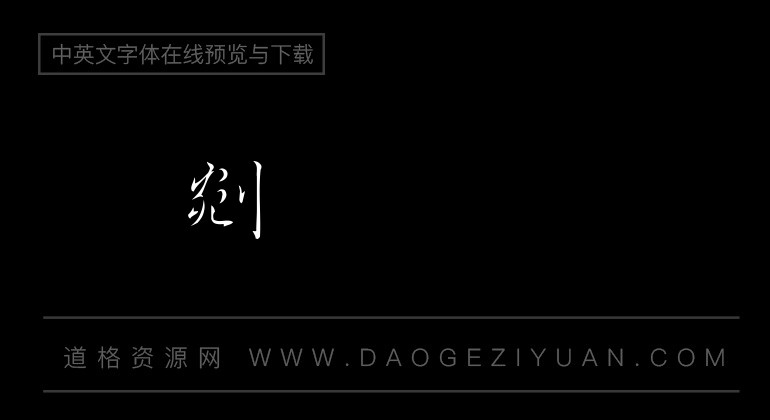
金梅毛草书
金梅毛草书是一种汉字字体,由梅兰竹菊组成,又称“金草书”。它的特点是字体粗犷,笔画粗犷,笔画粗犷,线条流畅,笔画清晰,曲线优美,表现力强,笔画平滑,视觉效果细腻,字形清晰,给人以清新自然、活泼生动的感觉。
金梅毛草书是一款非常不错的手写艺术字体,具有很好的视觉感,适合于文化类的宣传设计、商业类品牌的广告和产品包装设计以及个性化文字排版等较多场景。